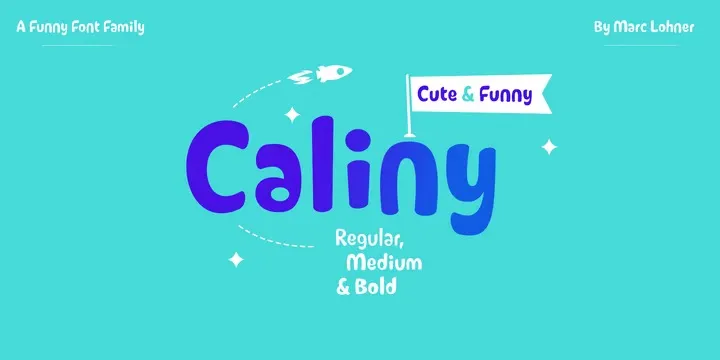
A Caliny Font é uma escolha incrível para qualquer projeto que deseje dar vida a um visual encantador e descontraído. Criada pelo designer Marc Lohner, essa tipografia de destaque tem uma atmosfera leve e encantadora. Perfeito para apps infantis, livros, jogos, embalagens, filmes, parques temáticos e tantas outras ideias criativas. Ideal para quem deseja dar vida a projetos infantis com um toque divertido de estilo único. Caliny é uma ótima opção para aqueles buscando um visual amigável e cativante para seus projetos digitais.